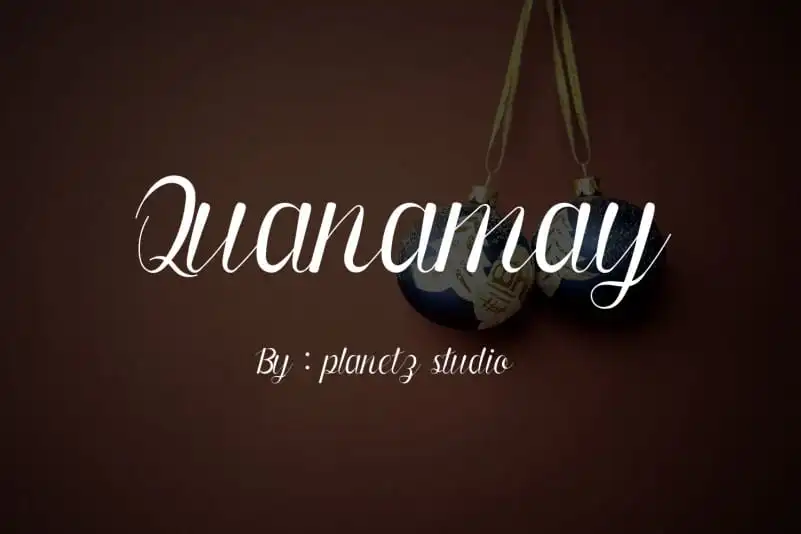
Quanamay Handwritten Font – Download Grátis
A Quanamay Handwritten Font é uma tipografia feita à mão com um toque suave e alegre que se destaca por sua facilidade relaxada e elegante. Suas linhas fluidas e personalizadas são ideais para criar designs de logotipos, marcas, cartões de casamento, arte de estação, postagens visíveis nas redes sociais e cartas de cumprimento encantadoras. Essa fonte é perfeita para designers buscando um toque humano em seus trabalhos, seja ele para criar identidades empresariais envolventes ou mensagens criativas no estilo do cotidiano. Ela traz uma vibe descontraída e autêntica à sua produção visual, tornando-a uma escolha perfeita para qualquer projeto onde o texto adquire um charme próprio.